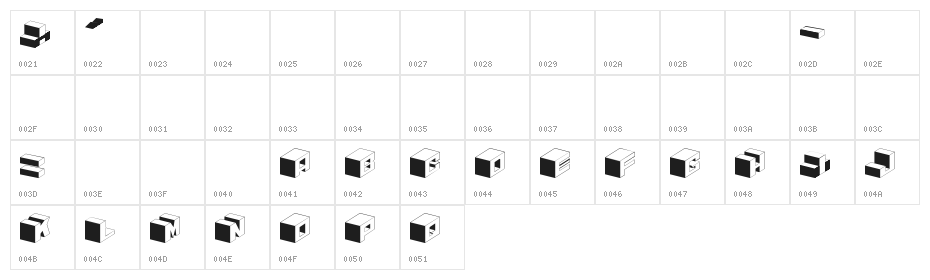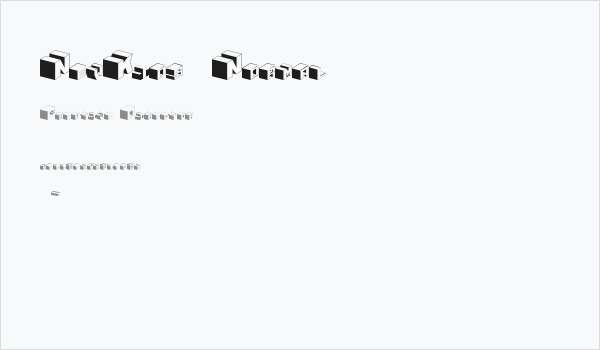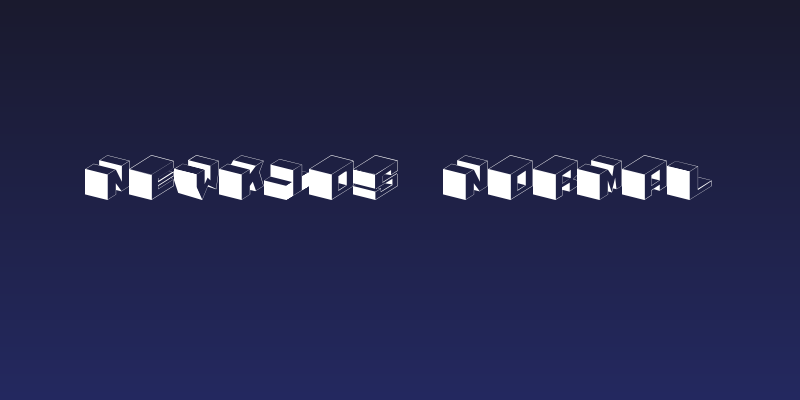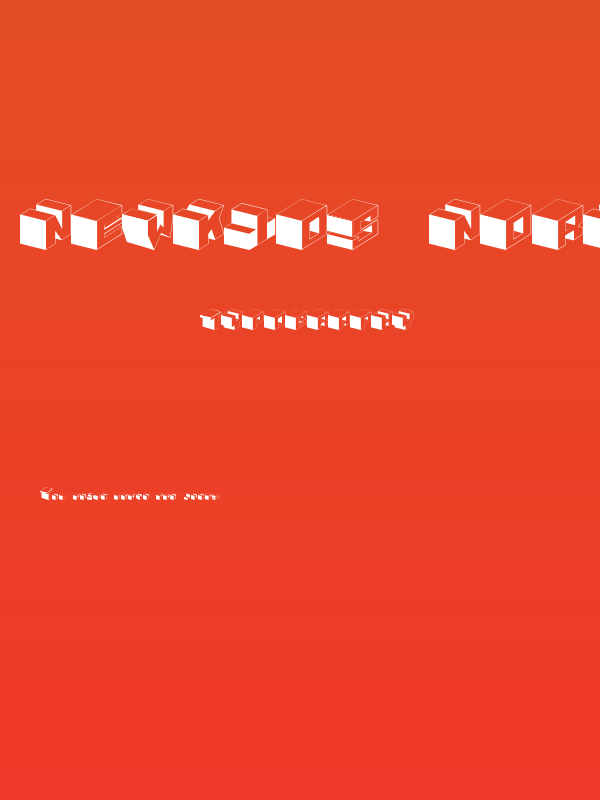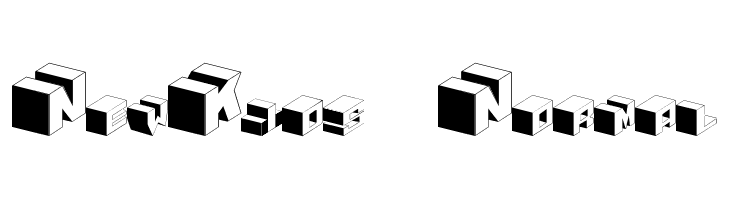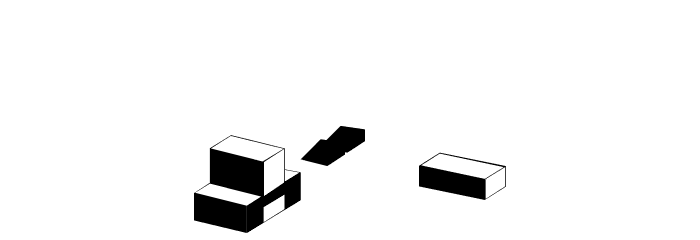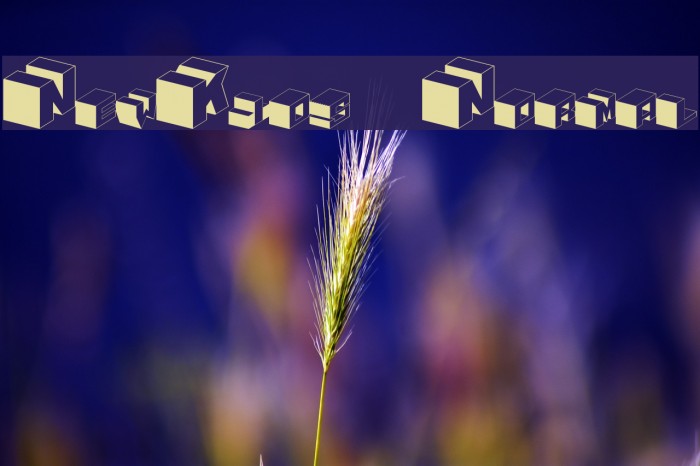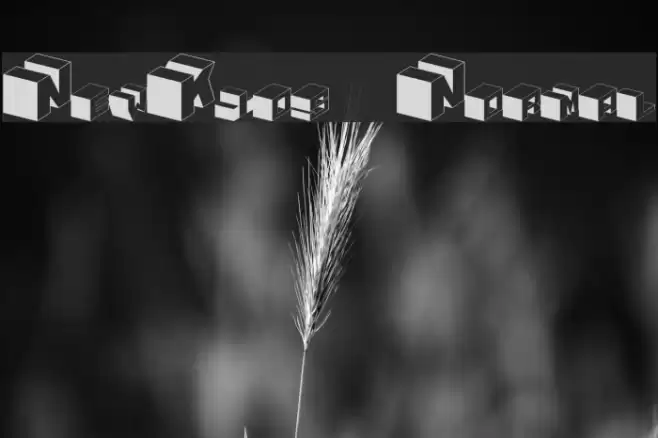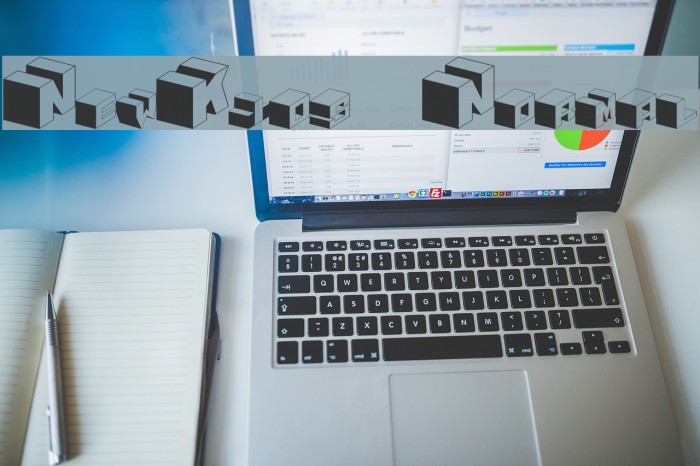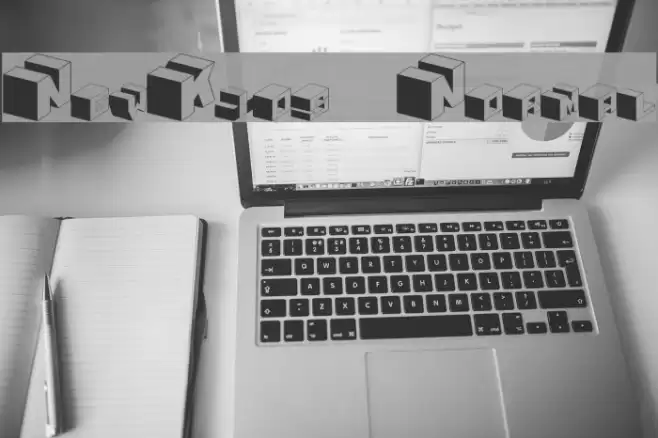
NewKids Normal Font
✎ 3D
| Gesamtstil | Retro, Playful |
| Vorgeschlagene Projekte | Ideal for video game titles, comic book covers, posters, and any project requiring a bold, playful aesthetic. |